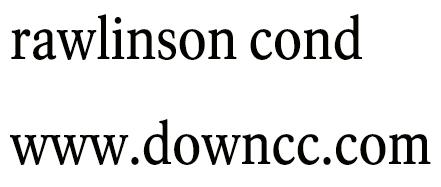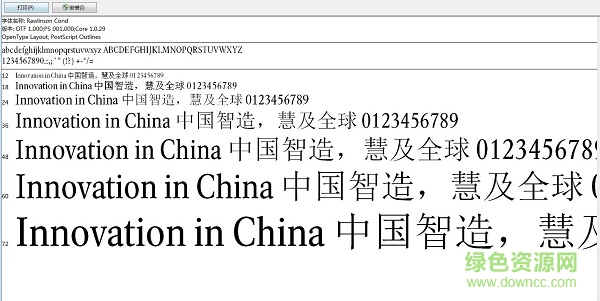
rawlinson cond字體是一款結(jié)構(gòu)端正嚴(yán)謹(jǐn)?shù)?a href="http://m.lz0519.com/k/chenxianziti/" target="_blank">襯線字體,字形穩(wěn)重,線條連貫順暢,字符間距得當(dāng),形成不錯(cuò)的韻律感,適用于平面設(shè)計(jì)、雜志標(biāo)題等方面,歡迎大家下載!